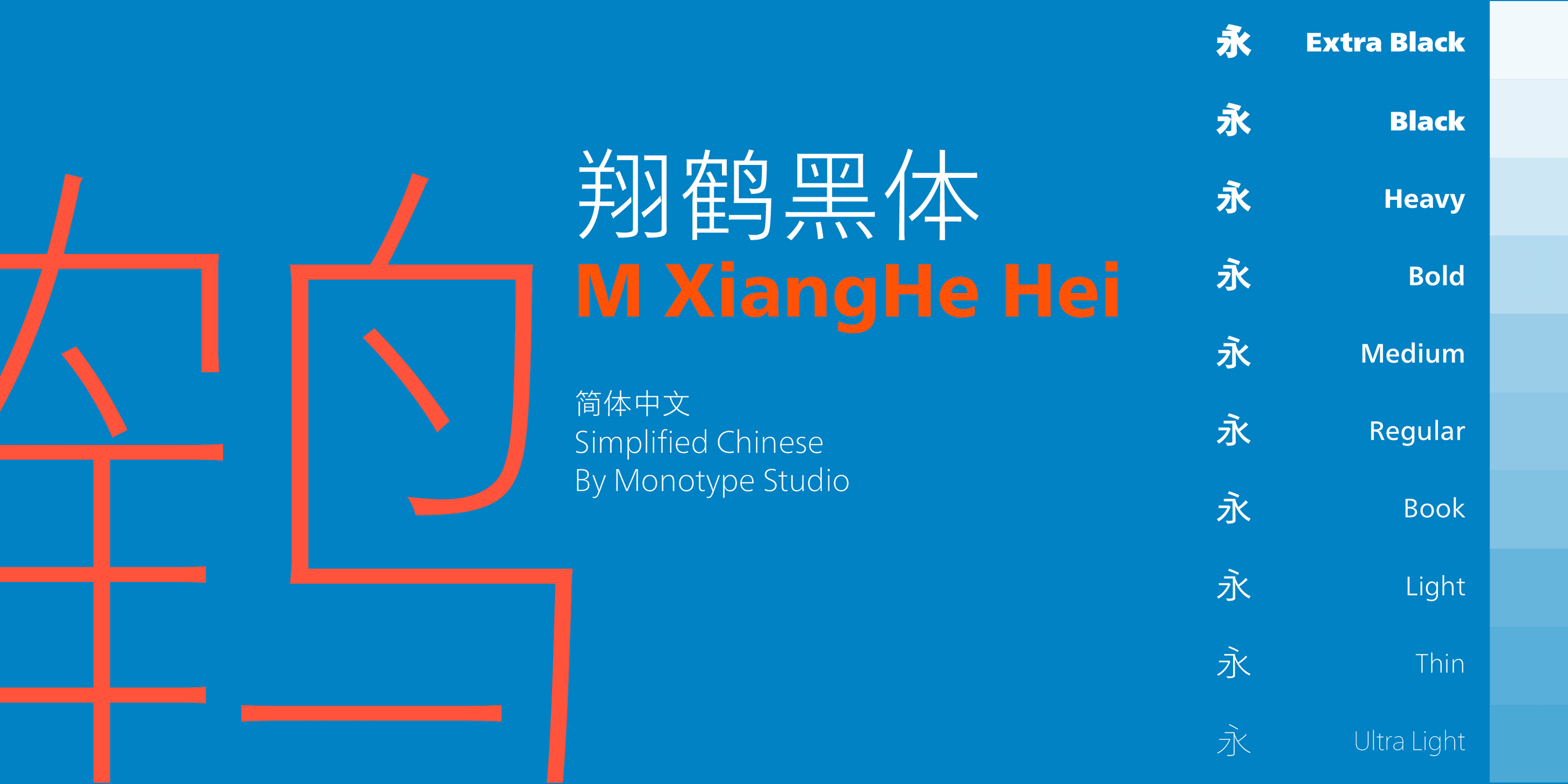
중국어 폰트
다양한 스타일, 폭넓은 디자인
모노타입의 중국어 폰트는 자획의 특징과 활용도를 기준으로 네 가지 유형—고딕, 등선, 필기, 도안—으로 분류되어 있어, 디자이너가 원하는 서체를 더 쉽게 찾을 수 있습니다.
M Ying Hei PRC
디지털 시대를 위한 서체
모노타입의 ‘잉흑체’는 기존 ‘모노타입 흑체’를 기반으로, 디지털 환경과 작은 화면에서도 뛰어난 가독성과 현대적인 이미지를 제공하도록 설계된 중국어 산세리프 서체입니다. 넓은 중궁과 다양한 웨이트로 다양한 브랜드 서체와 잘 어울리며, 빠른 정보 전달에 최적화되어 있습니다.
더 알아보기 M XiangHe Hei
두루미처럼 우아한 서체
모노타입의 ‘잉흑체’는 기존 ‘모노타입 흑체’를 기반으로, 디지털 환경과 작은 화면에서도 뛰어난 가독성과 현대적인 이미지를 제공하도록 설계된 중국어 산세리프 서체입니다. 넓은 중궁과 다양한 웨이트로 다양한 브랜드 서체와 잘 어울리며, 빠른 정보 전달에 최적화되어 있습니다.